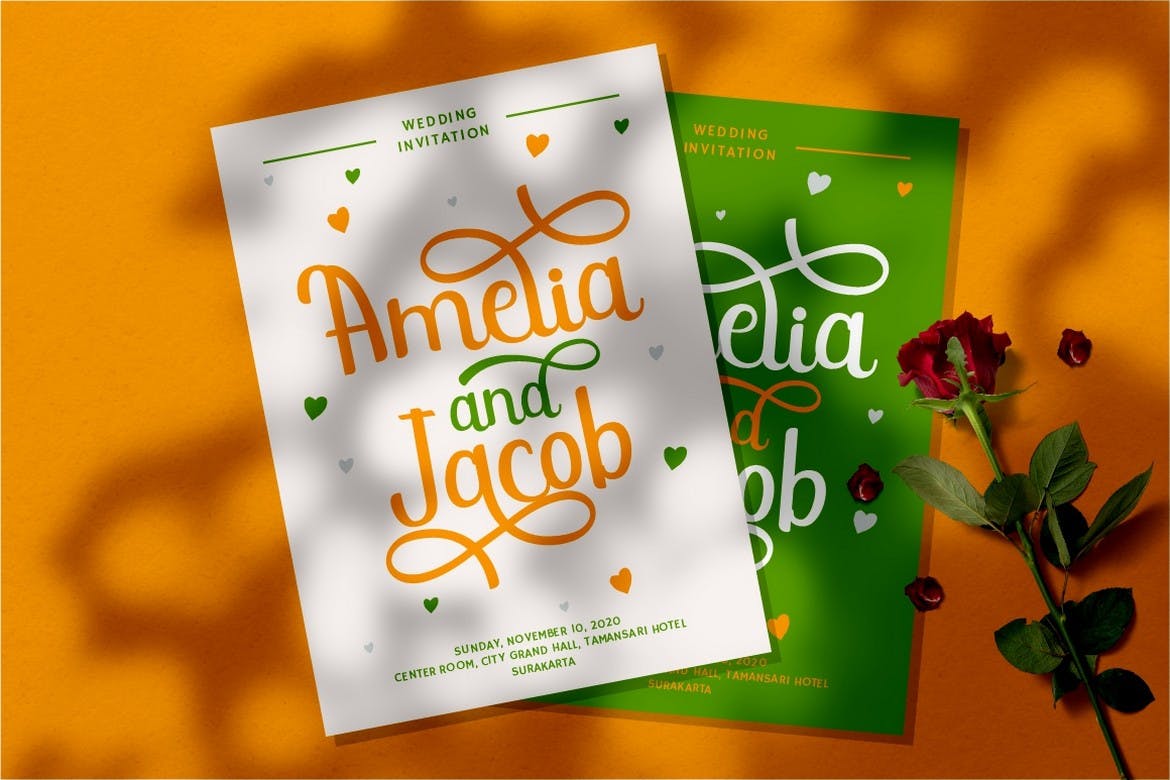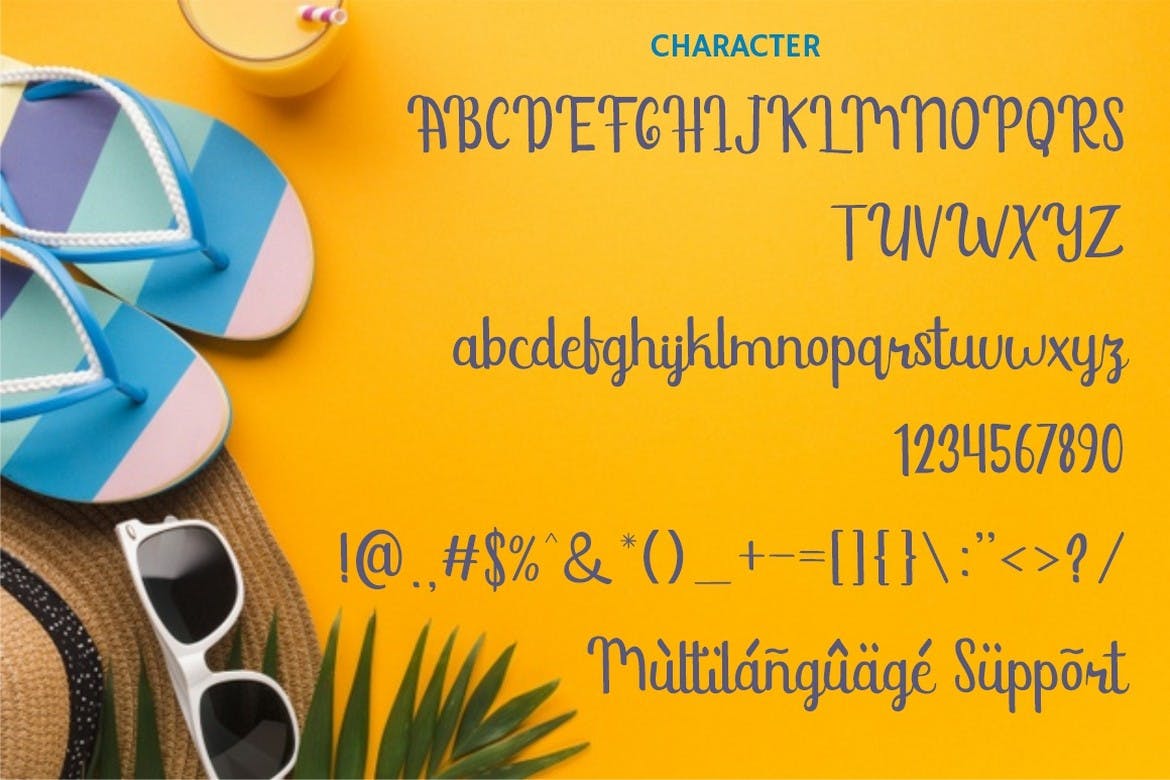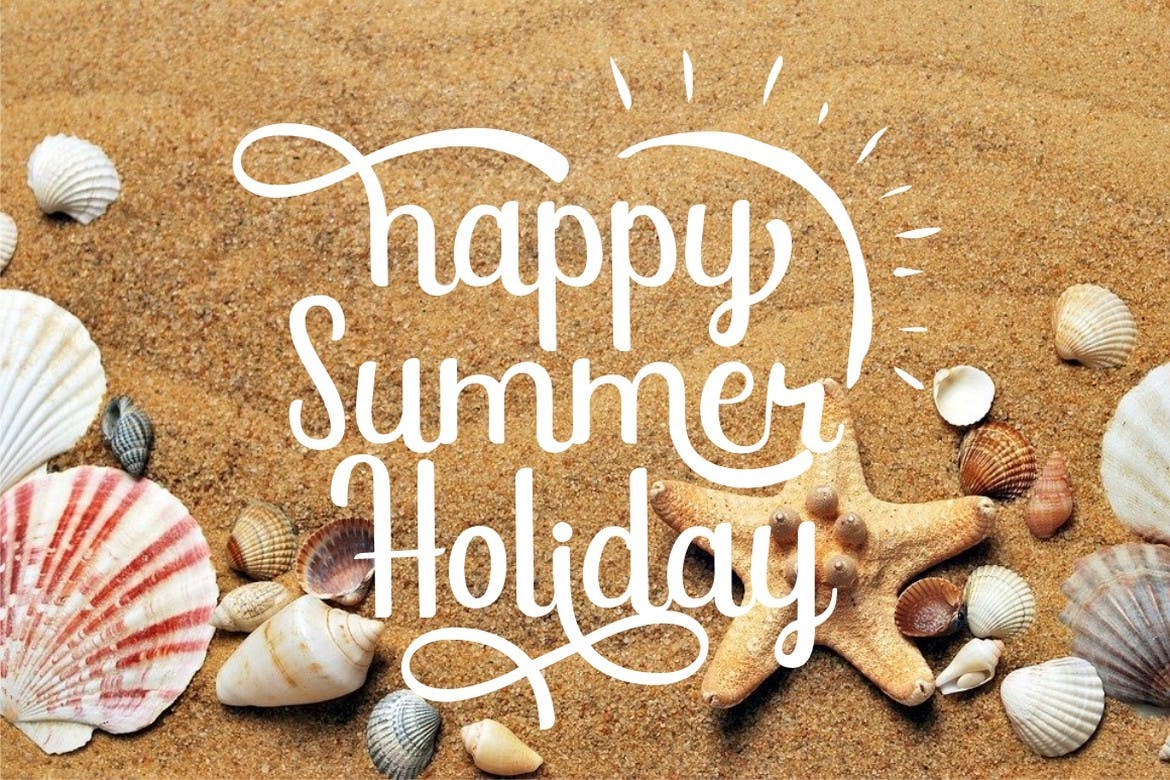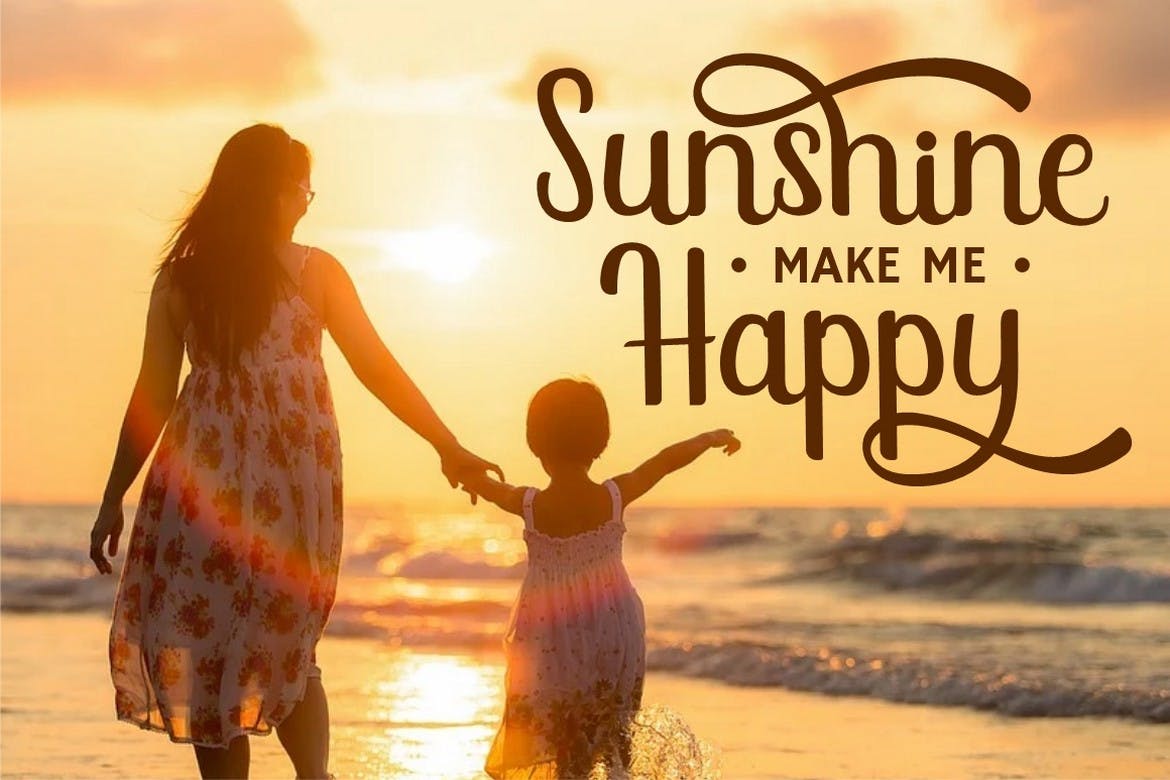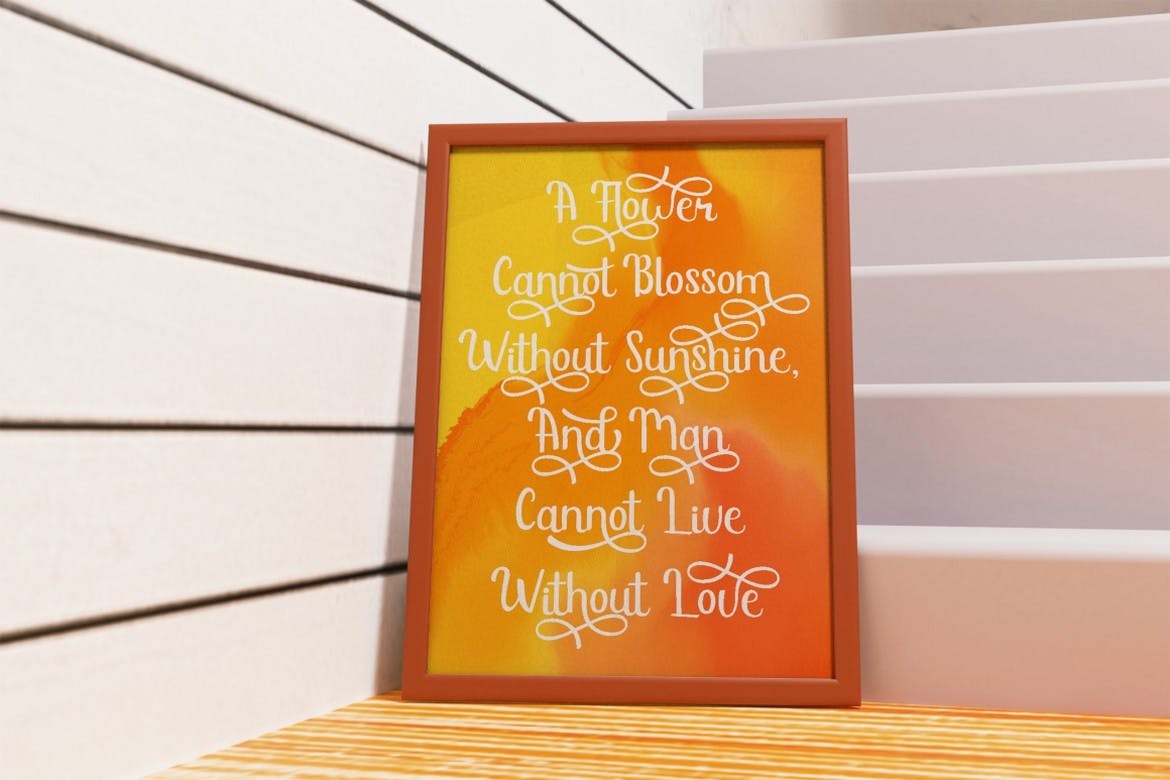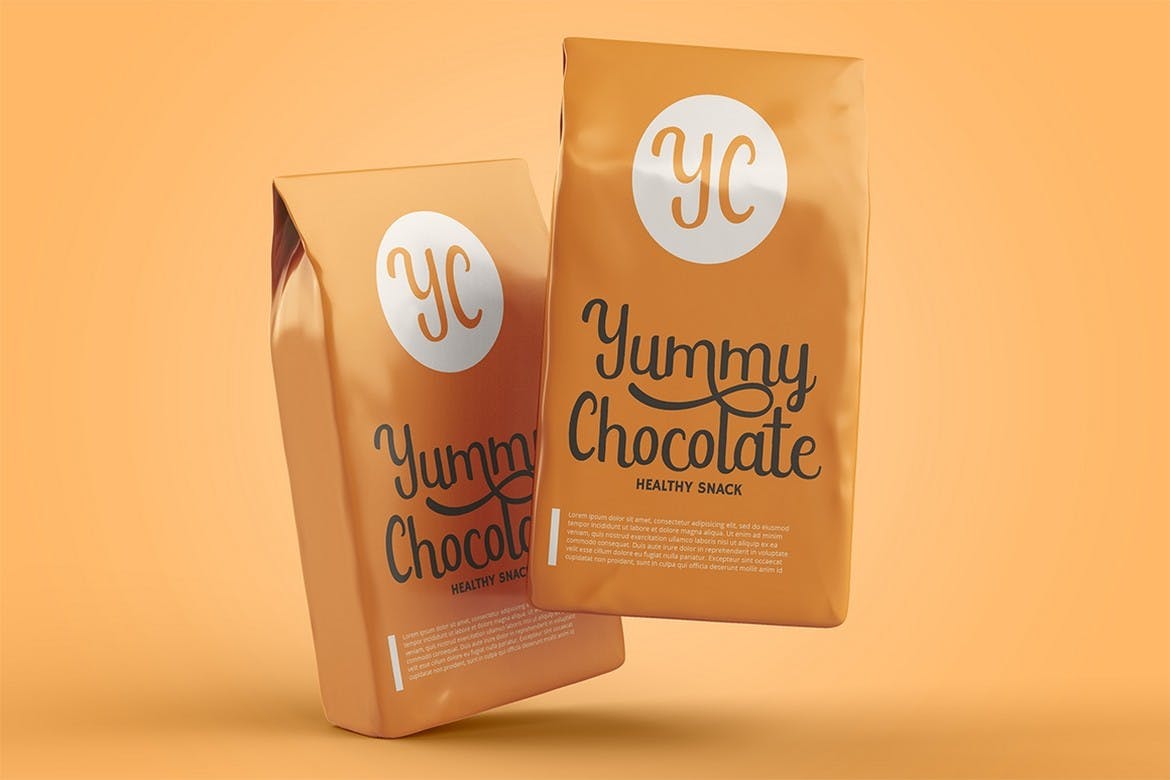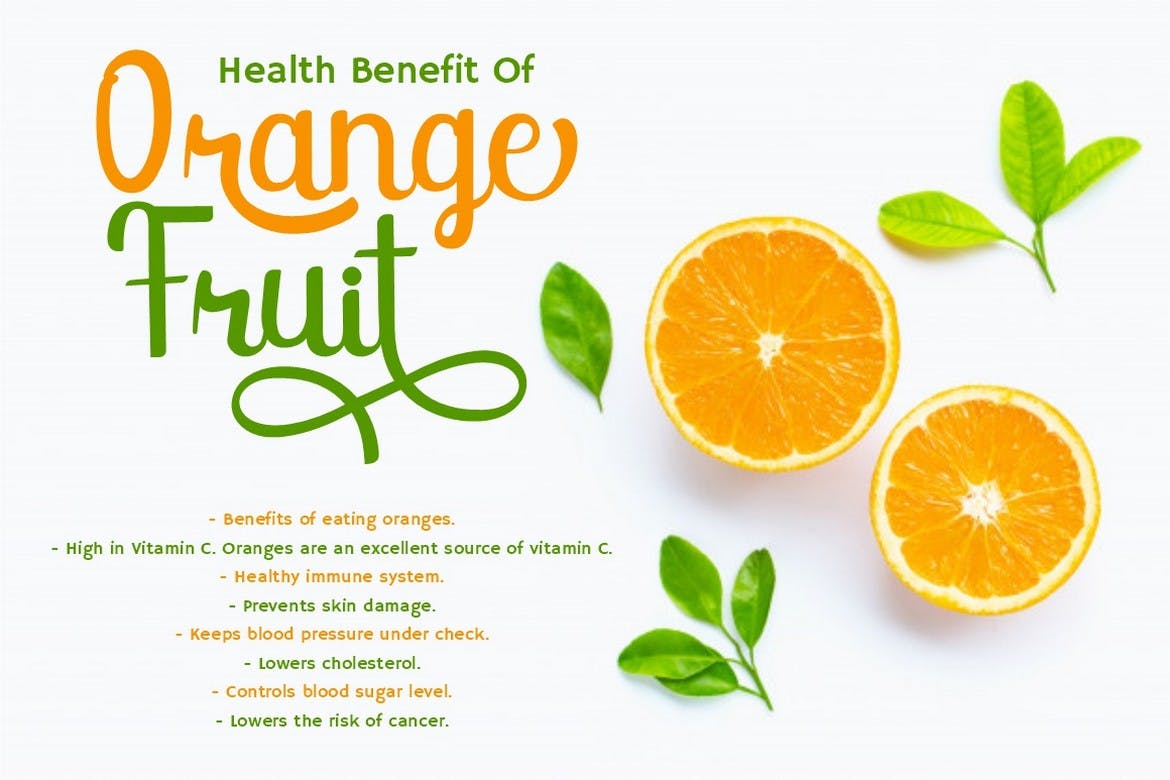
Sunshine Mind Display Script Font
فونت Sunshine Mind، انتخابی ایده‌آل برای پروژه‌های خلاقانه شما.
فونت Sunshine Mind
فونت Sunshine Mind یک فونت نمایشی و اسکریپت است که به‌خصوص برای طراحان و خالقان آثار هنری مناسب می‌باشد. این فونت برای طراحی‌های مختلفی مانند طراحی‌های دستی، طراحی‌های SVG، ایجاد لوگو، ترکیب حروف، دعوت‌نامه‌های عروسی، پروژه‌های مد، طراحی جلد کتاب، تایپوگرافی مجلات، کارت‌ها، بسته‌بندی‌ها، پوسترها، برندینگ و بسیاری دیگر ایده‌آل است. همچنین این فونت از چندین زبان پشتیبانی می‌کند.
ویژگی‌های فونت:
• حروف بزرگ
• حروف کوچک
• حروف جایگزین
• اعداد، نشانه‌گذاری و نمادها
• پشتیبانی از چند زبان